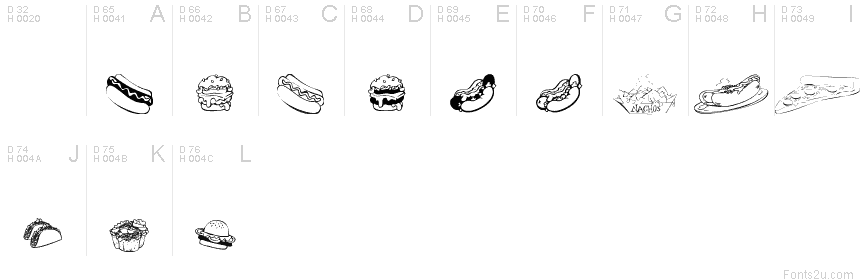
KR Fast Food от Kat Rakos — это бесплатный дингбат-шрифт с выразительными line-art иллюстрациями бургеров, хот-догов, картошки фри и многого другого. Каждая иконка выглядит как рисунок от руки, с плотными, «тушевыми» контурами и живыми изгибами, которые отлично читаются даже в мелком размере. Графика сохраняет игривый баланс между мультяшным стилем и узнаваемостью, поэтому ваш клиент сразу поймет, что в меню.
Используйте KR Fast Food, чтобы оживить меню, брендинг фуд-траков, листовки для кафе, детские задания, карточки с рецептами, наклейки и посты в соцсетях. Иконки легко вставлять как отдельные иллюстрации или как повторяющиеся паттерны без ощущения перегруженности. Этот бесплатный шрифт отлично сочетается с простым гротеском в основном тексте; старайтесь использовать KR Fast Food чуть крупнее, чем остальной шрифт, чтобы аппетитные детали оставались четкими и вкусными.